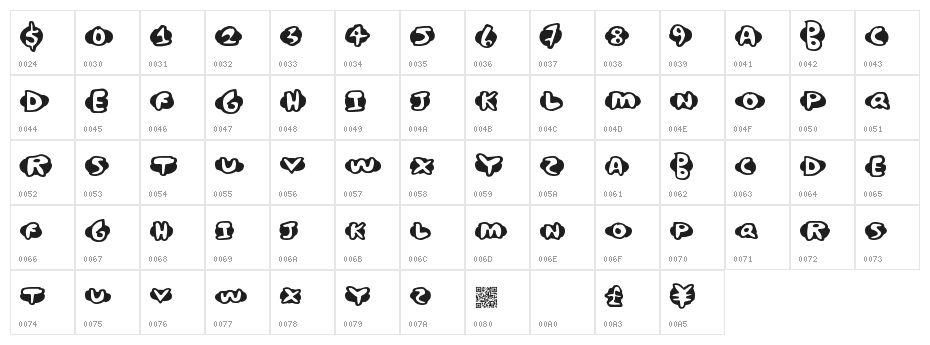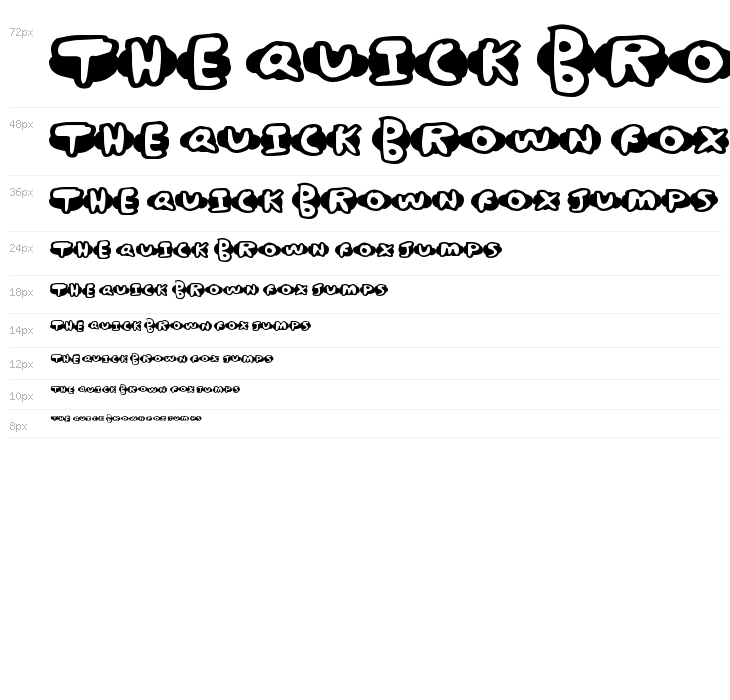
ChickenWaffles Font
CHICKENWAFFLES MAIUSCOLE
CHICKENWAFFLES MINUSCOLO
CHICKENWAFFLES ALTRI CARATTERI
| Stile generale | Playful, Cartoonish |
| Progetti proposti | Ideal for children's books, comic strips, playful branding, and creative posters. |